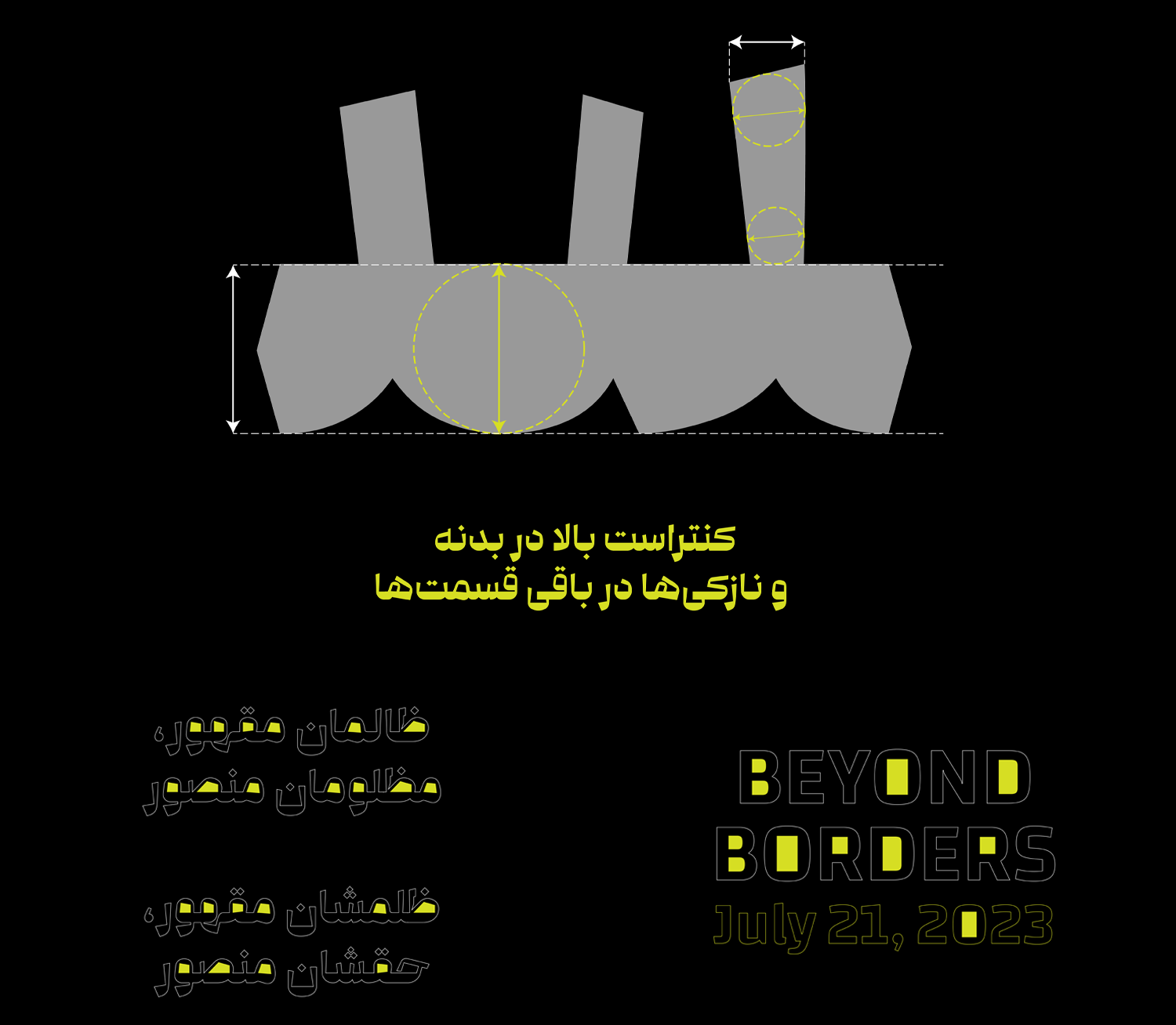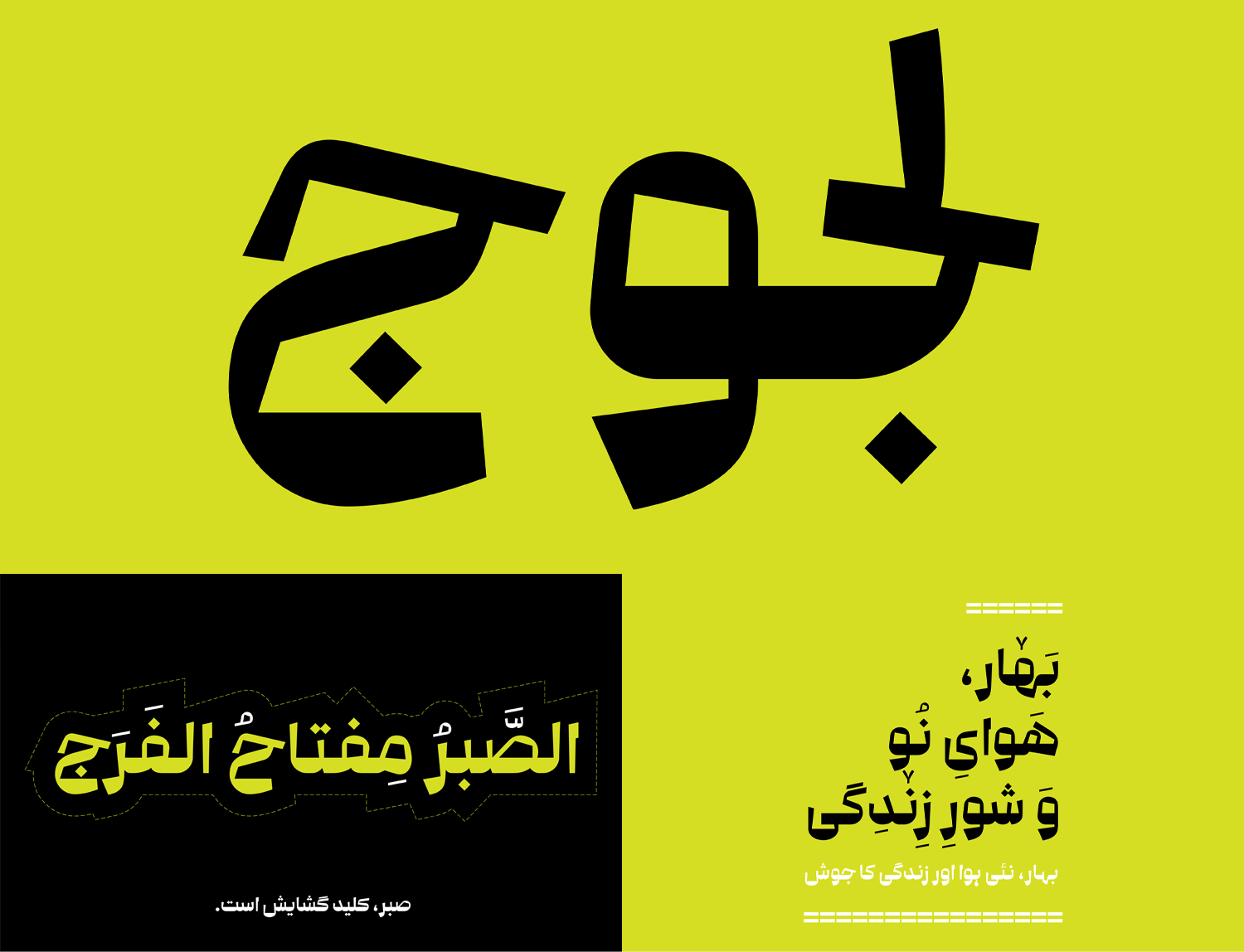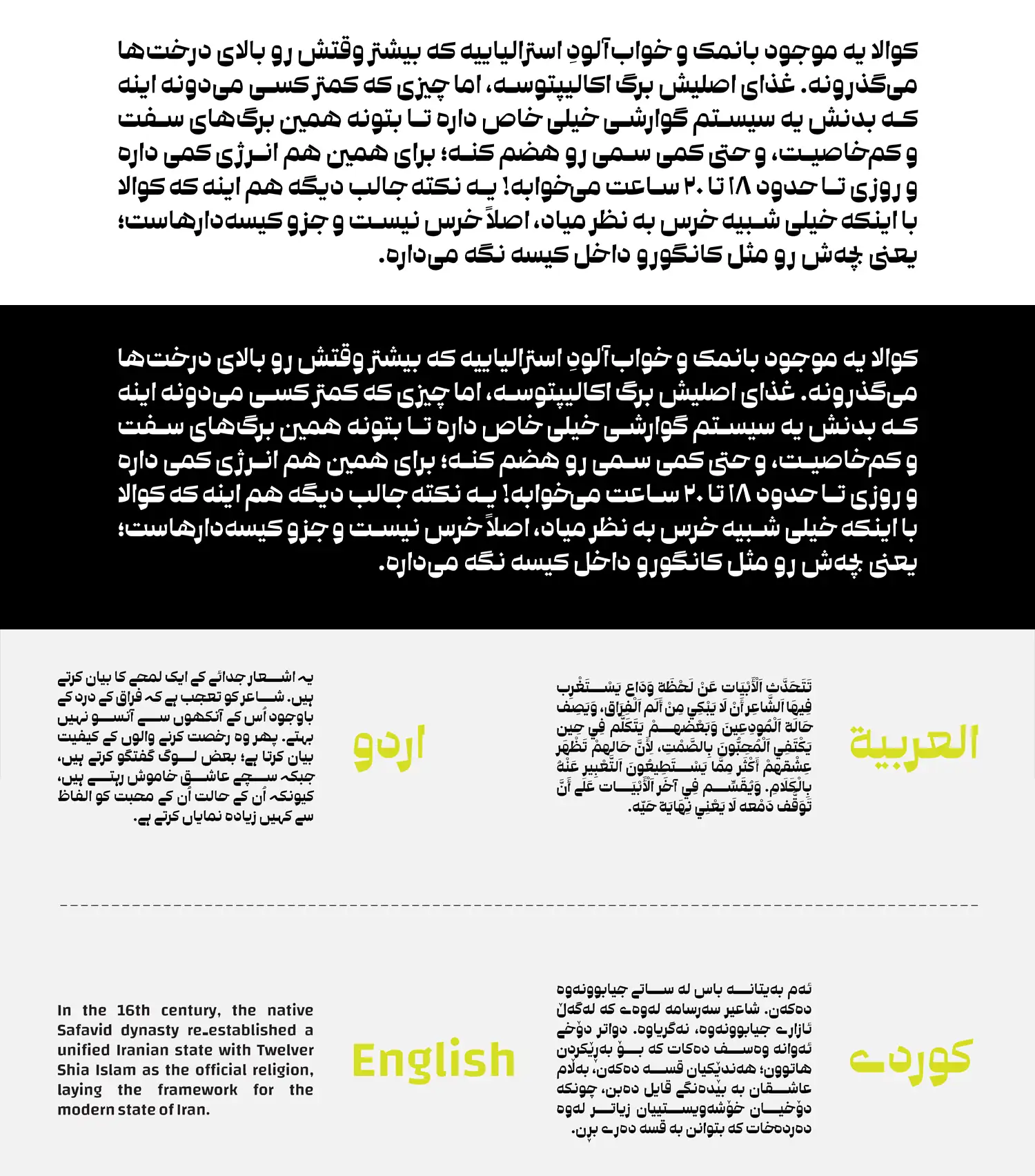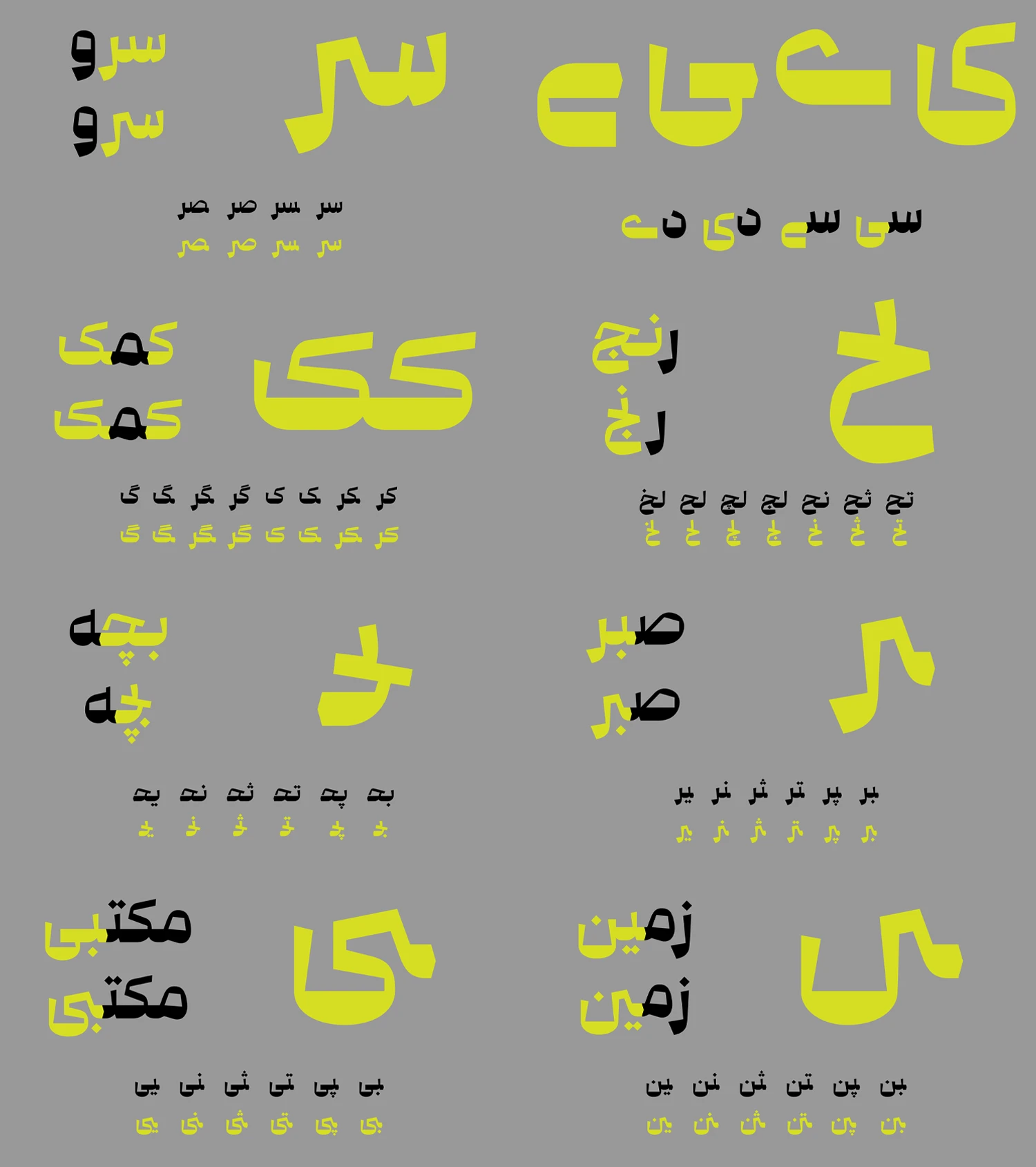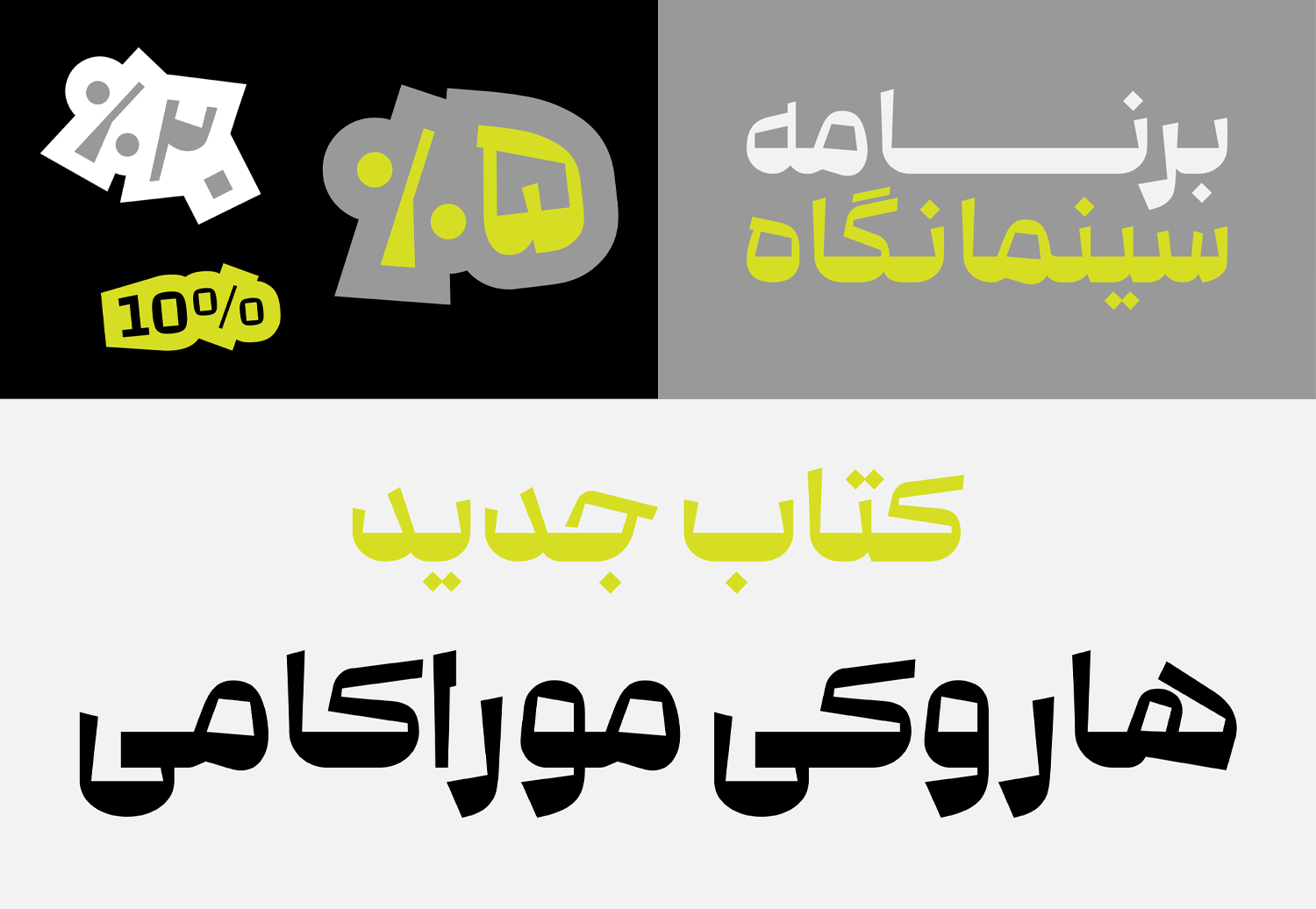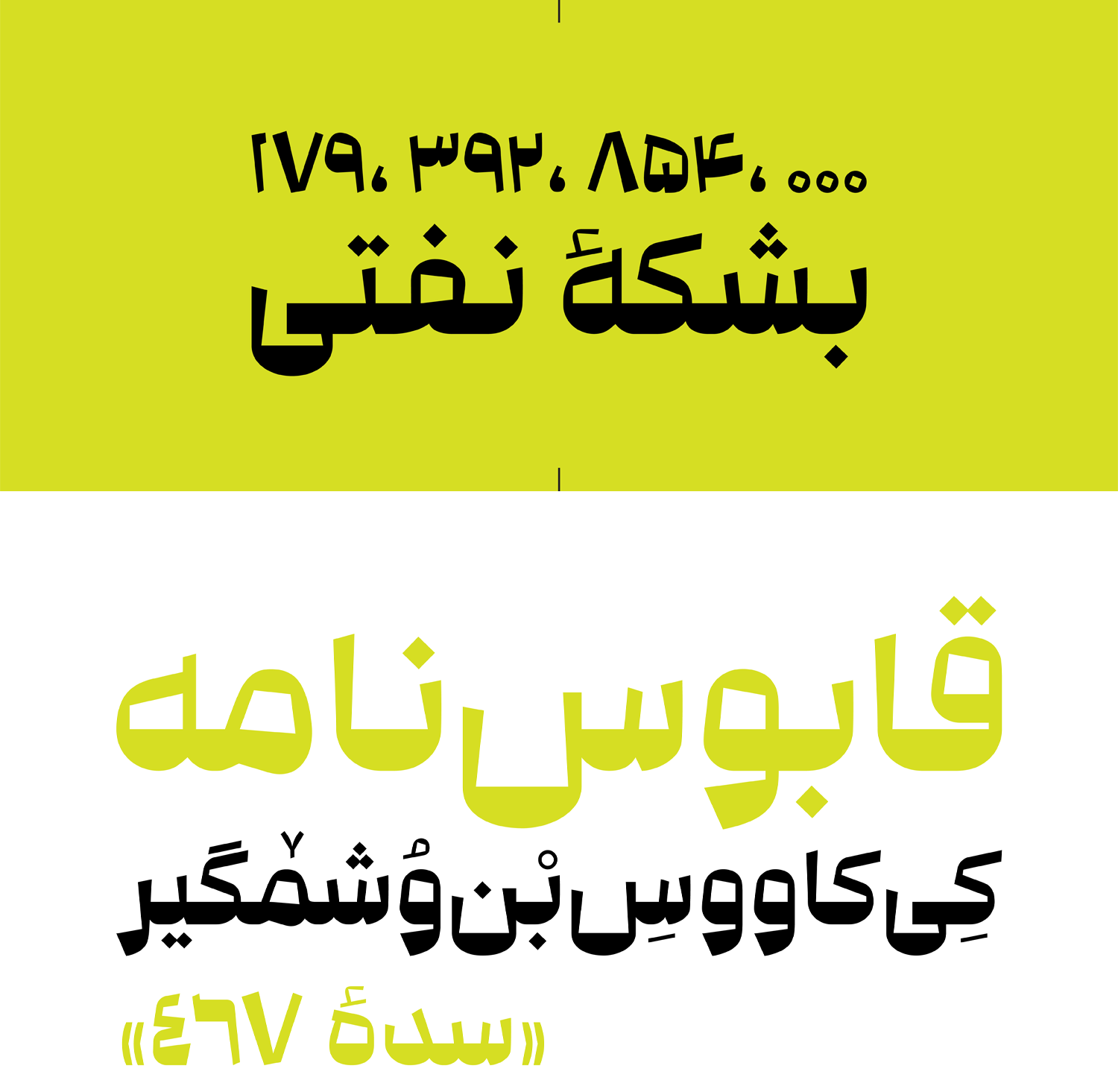
فونت کوآلا (Kowala)
| طراح | یاسر عزآباد |
فونت کوآلا (به انگلیسی: Kowala) از سری فونتهای جید فارسی با ساختاری هندسی است که با فرم هایی شکسته، ظاهری استوار و منظم را در عین بازیگوشی و شخصیت دوستداشتنی خود حفظ کرده است. در این فونت فارسی با تناسبی در ساختار مختلف حروف مواجهیم که بسیار اغراق شده هستند. اگر به دنبال شخصیتی از این ساختار با چشمهای درشت باشیم، کوآلا با دست و پای بلند معرف آن است.
یاسر عزآباد در طراحی این فونت، وزن و استحکام بدنه اصلی را در خط پایینی حروف قرار داده، در حالی که خطوط بالایی رفتهرفته نازکتر میشوند. همین نازکی به فرمها و چشمی حروف، شخصیت روان و سبکتری میدهد. دایرهها و چشمی حروف این فونت با ساختار هندسی شکسته و تند خود، تضادی را در مقایسه با فضای بیرونی فونت ایجاد کرده که پویایی و شخصیت فونت را بیشتر از پیش میکند.
با چنین توصیفاتی از فونت کوآلا میتوانید در عناوین و تبلیغات بهترین استفاده را داشته باشید. طراحی انواع پوستر، جلد کتب و مجلات، عناوین Heading در فضای وب و طراحی بنرهای محیطی از محبوبترین کاربردهای این قلم فارسی است.
با اینکه فونت کوآلا دارای یک وزن سیاه (Black) است، اما در ظاهر خیلی هم سیاه به نظر نمیرسد و تعادلی را بین وزن خاکیتری و سیاه حفظ کرده است. این فونت تکوزن علاوه بر فارسی، از زبانهای انگلیسی، اردو، عربی و کوردی نیز پشتیبانی میکند.
پشتیبانی از هر زبان گلیفهای استاندارد خود را دارد. بهویژه اینکه در بخش اعداد شاهد دو نسخه متفاوت از فایل فونتها هستیم. یکی فایلهای معمولی که هر دو گلیف اعداد انگلیسی، عربی و فارسی را در خود دارند. و دیگری فایلهای مخصوص اعداد هک شده که در آنها، نسخه انگلیسی و عربی اعداد را هم که تایپ کنید، به شکل فارسی تایپ خواهند شد که برای توسعه و استفاده در نرمافزارها و سایتها مناسب هستند.
یکی از مثبتترین بخشهای فونت کوآلا، بخش حروف و ترکیبات جایگزین است. بدین معنی که میتوانید برخی ترکیبات حروف را در کلمات مختلف با چند ظاهر متفاوت تایپ کنید. این ویژگی اجازه میدهد بدون نیاز به صرف ساعتها زمان در برنامههای گرافیکی، ظاهر متفاوت از خط معمولی را به برخی کلمات بدهید که برای تبلیغات و فونتهایی در دسته عناوین، واقعا کاربردی هستند. در ادامه میتوانید پیشنمایشهای مختلفی از این فونت را مشاهده کنید.